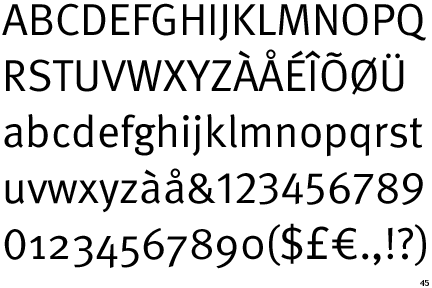
single storey a & binocular g (und auf deutsch?)
single storey a & binocular g
also so heissen die Dinger in englisch, aber ich bin grade doof und komm nich drauf wie die Dinger hier genannt werden!? Und wie werden die Gegensätze genannt? Also das double storey und ...?
Hallo Steven,
das ist im Englischen wie im Deutschen nicht verbindlich geregelt.
Eine übliche deutsche Bezeichnung für beide wäre offene bzw.
geschlossene Form, eine durchaus praktische Benennung.
Für das a ist auch der Import aus dem Englischen gebräuchlich
(ein- bzw. zweigeschossiges a), für das g empfinde ich die
Bezeichnungen ein- bzw. zweischleifig sehr elegant.
Ferner wird noch der Begriff Antiqua-a für die offene,
zweigeschossige bzw. Antiqua-g für die geschlossene,
zweischleifige Formvariante verwendet. Diese Benennung
verwende ich eher ungern, weil das Wort »Antiqua«
als Gegenmodell zu »Gebrochene Schriften« zu verstehen
ist, aber heute kaum noch jemand den Formenkanon der
gebrochenen Schriften intus hat. In der Sache stimmt es,
nur würde keiner mehr mit den Gegenbegriffen was anfangen
können (pauschalierend: Fraktur-a).
So, zu Englisch schreibt jemand anderer.
H.
Und wie werden die Gegensätze genannt? Also das double storey und ...?
Wenns mit dem binocular g so einfach ist, wie mit single/double storey, dann ists wohl ein monocular g.
Norbert
Schnell im Webster's nachgeschlagen: monocular = having only one eye
Als Monokel-g passte das so gesehen perfekt zu Andreass' Brillen-g.
Norbert Riedi
Würde gerne noch einmal dieses alte Thema hochholen. Bekommen wir in dieser Hinsicht einen Konsens für vernünftige Begriffe hin?
Ich habe es gerade bezüglich des Englischen nochmal nachgefragt:
Wie dort beschrieben: Wenn das a mal ein- und mal zweistöckig sein kann, kann das meiner Meinung nach nicht für das g gelten. Also wie sagt man’s klar und verständlich?
Vorschläge:
verschleiftes (geschleiftes?) und einfaches/offenes g
überdachtes/zweistöckiges und einfaches/einstöckiges a
Aus schriftgeschichtlicher Sicht kann man, wie oben schon geschrieben, die humanistischen Formen/Antiqua-Formen (überdachtes a, verschleiftes g) und die Kursiv-/Frakturformen (einstöckiges a, offenes g) unterscheiden.
einstöckiges ›a‹:
zweistöckiges ›a‹:
zweistöckiges ›g‹:
dreistöckiges ›g‹:
einstöckige ›g‹ gibt es nicht, weil die buchstabenform das nicht vorsieht.
ich sehe das problem, dass sich bei ›a‹ beide stockwerke innerhalb der x-höhe befinden, während das unterste stockwerk bei ›g‹ die unterlänge ist. trotzdem würde ich sagen: stockwerk ist stockwerk. so weit meine vorschläge.
Ja, genau so würde ich das auch sagen.
Aber das deckt sich eben nicht mit üblichen Definitionen: http://desktoppub.about.com/cs/typeanatomy/g/double_g.htm
Wenn man also »zweistöckig« benutzt, muss man immer gleich dazusagen, »welches zweistöckig« man denn nun meint. Das macht die Verwendung solcher Begriffe ja ziemlich nutzlos.
dir geht es also um einen begriff, der ›ɑ/ɡ‹ (futura) gemeinsam von ›a/g‹ (melior) abgrenzt? ich glaube, dass die verbreitetste terminologie ›einstöckig‹ für zwei unterschiedlich strukturierte buchstaben, nämlich ›ɑ‹ (meines erachtens wirklich einstöckig) und ›ɡ‹ (meines erachtens zweistöckig), verwendet. der nachteil dieser variante ist: es bleibt unklar, was ein stockwerk ist, sodass man den begriff nicht für andere buchstaben verwenden kann.
innerhalb der jeweiligen buchstaben ist unabhängig von der verwendeten terminologie jeweils klar, was gemeint ist: ›a‹ ist unproblematisch, da es selbst bei genauer zählung keine dreistöckigen ›a‹ gibt. beim ›g‹ ist es etwas schwieriger, aber da es keine einfachere form als ›ɡ‹ (futura) gibt, meint jemand, der von einem einstöckigen ›g‹ spricht, offensichtlich diese. jemand, der von einem dreistöckigen ›g‹ spricht, muss dagegen das meinen, was andere als ›zweistöckig‹ bezeichnen, weil es keine komplexere form gibt. der nachteil dieser variante ist: die subjektive zusammengehörigkeit von ›ɑ‹ und ›ɡ‹ (futura) bzw. ›a‹ und ›g‹ (melior) wird nicht ausgedrückt.
man könnte ›ɑ‹ und ›ɡ‹ (futura) als einfache formen oder handschriftformen bezeichnen. ›a‹ und ›g‹ (melior) wären dann komplexe formen oder buchdruckformen. ›ɑ‹ und ›ɡ‹ könnte man auch schulbuchformen nennen, aber mir fällt kein entgegengesetzter begriff für ›a‹ und ›g‹ ein.
keine ahnung, ob das irgendwas hilft. über die englischen bezeichnungen habe ich noch nicht nachgedacht.
›a‹ ist unproblematisch, da es selbst bei genauer zählung keine dreistöckigen ›a‹ gibt.
Sachdoch sowas nicht ...
Ich sehe beim ›a‹ doch eindeutig ein Erdgeschoß, ein erstes Obergeschoss und das zweite Obergeschoss als Dachgeschoss, zusammen drei Stockwerke in diesem Hause... Beim ›ɑ‹ nur Erdgeschoss und Dachgeschoss, also zweistöckig, und beim ›ɡ‹ Dach-, Erd- und Kellergeschoss, also 3, und beim ›g‹ zwei Untergeschosse, also 4 Etagen ... ;-)
somit ist das ɡ einstöckig, weil die untere form nicht geschlossen ist?
offen und geschlossen sind für mich die logischsten begriffe.
somit ist das ɡ einstöckig, weil die untere form nicht geschlossen ist?
Nee, das Stockwerk kann ja an einer Seite eine offene Front mit Blick auf die Stadt haben! :-)
offen und geschlossen sind für mich die logischsten begriffe.
Und was ist dann mit dem Meta-g? Ist ja klar die »Brillenform«, aber unten eben auch »offen«. Damit kommt man auch nicht so richtig weiter.